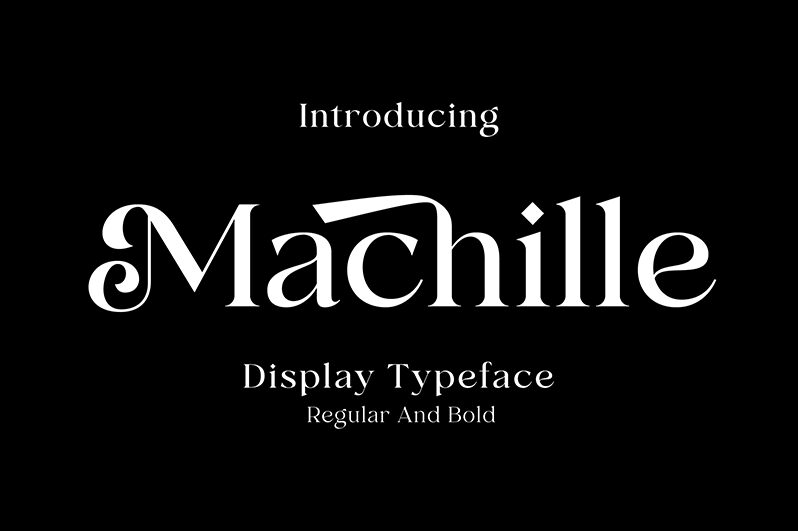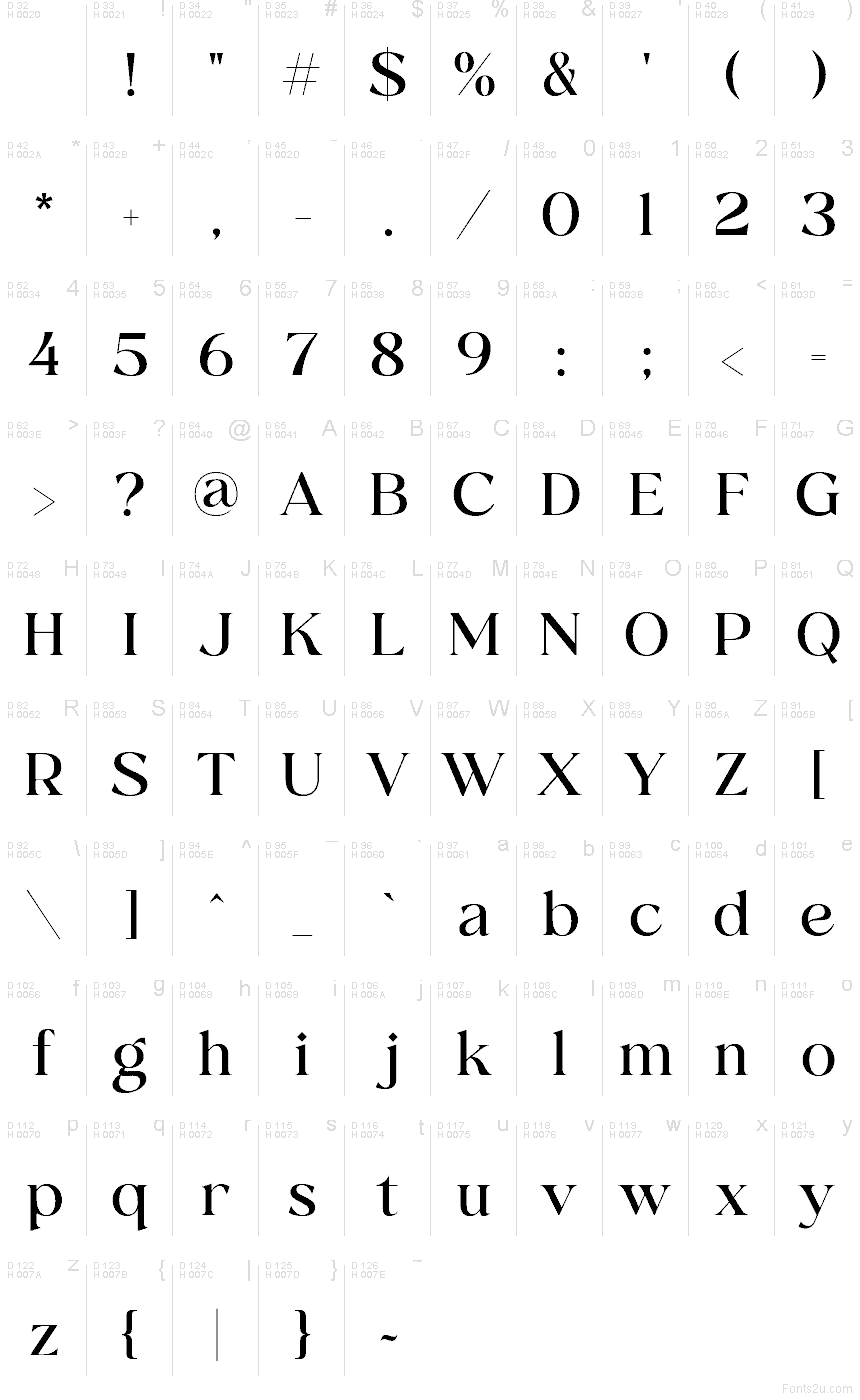
Criada por Akhmad Reza Fauzi, a Machille Bold é uma fonte serifada gratuita de alto contraste, com um ar imponente de editorial de moda. Suas maiúsculas amplas combinam traços ultrafinos a hastes verticais encorpadas e cortadas com precisão, enquanto as letras arredondadas exibem curvas especialmente generosas. Serifas finas e sem concordância conferem às formas um acabamento nítido e elegante.
A capa de uma revista de moda é o seu ambiente mais natural, onde a variação extrema na espessura dos traços remete aos cabeçalhos de publicações de luxo e à identidade visual das passarelas. Esse mesmo impacto formal valoriza embalagens de perfumes e o design de convites, sobretudo quando a tipografia precisa transmitir sofisticação sem perder a força gráfica. A identidade visual de restaurantes e cartazes de eventos culturais oferecem outro caminho muito promissor, explorando as proporções imponentes e as curvas dramáticas da fonte.